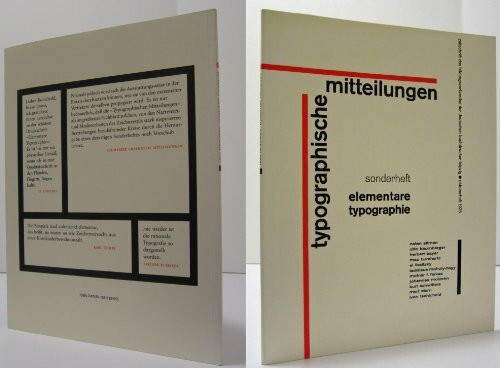
Elementare Typografie: Sonderheft der Typografischen Mitteilungen 1025
"Elementare Typografie: Sonderheft der Typografischen Mitteilungen 1025" von Jan Tschichold ist ein wegweisendes Werk, das sich mit den Prinzipien und der Entwicklung der modernen Typografie auseinandersetzt. In diesem Buch präsentiert Tschichold seine Ansichten zur Neuen Typografie, die in den 1920er Jahren entstand und sich durch ihre funktionale und klare Gestaltung auszeichnet. Das Buch betont die Bedeutung von Klarheit, Lesbarkeit und Funktionalität in der typografischen Gestaltung und stellt einen Bruch mit traditionellen, dekorativen Stilen dar. Tschichold propagiert den Einsatz asymmetrischer Layouts, standardisierter Schriftarten und einer reduzierten Farbpalette, um eine maximale visuelle Wirkung zu erzielen. Dieses Sonderheft ist ein bedeutender Beitrag zur typografischen Literatur und spiegelt die avantgardistischen Strömungen seiner Zeit wider. Es richtet sich an Designer, Künstler und Typografen, die sich für die Grundlagen der modernen Gestaltung interessieren.